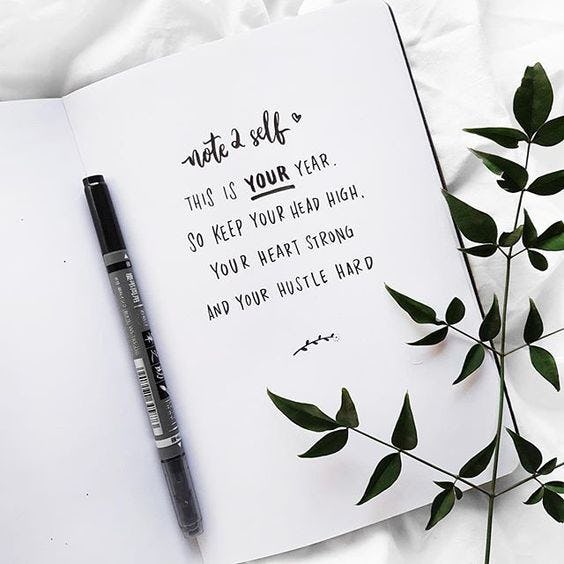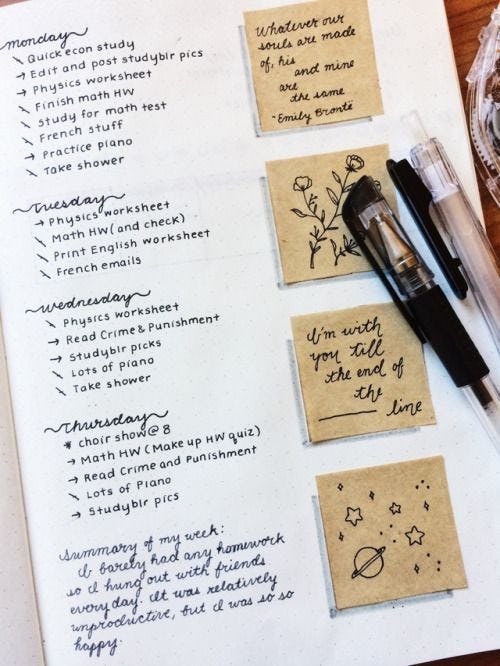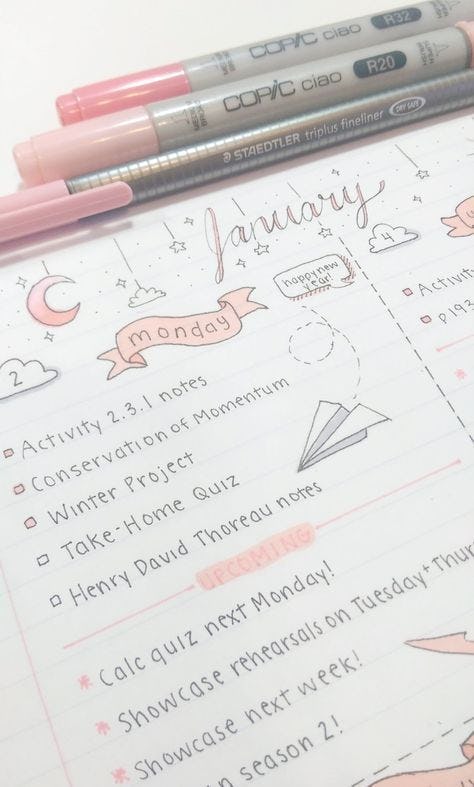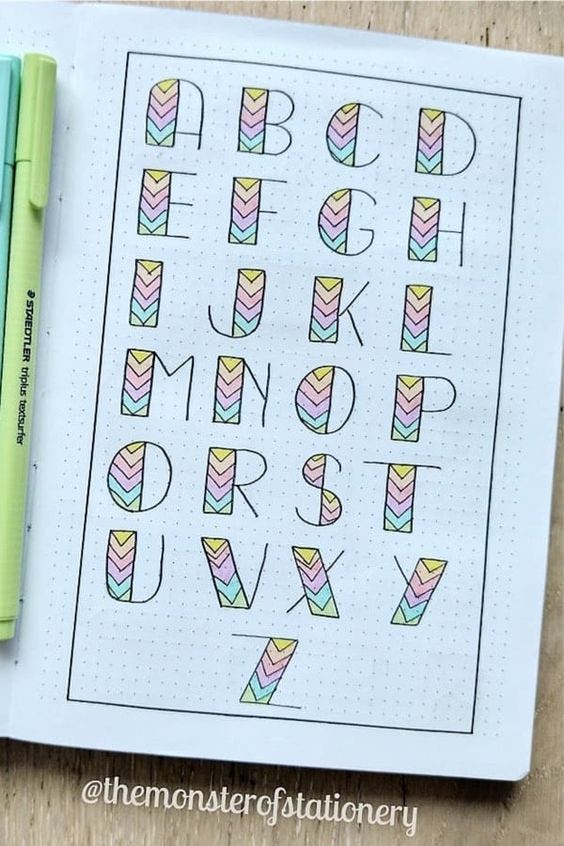
En otro artículo te contamos todo sobre el bullet journal: qué es, cómo hacerlo y para qué sirve. Hoy, te traemos las bullet journal fonts más lindas para que puedas empezar de inmediato a armar tu propia libreta.
En este artículo encontrarás más de 60 letras para bullet journal de las que te vas a enamorar. No hace falta que te dediques a la ilustración, con un poco de paciencia lograrás increíbles tipografías y tu bullet journal quedará espectacular.
¿Cómo elegir letras para bullet journal?
Si ya estuviste mirando algunos ejemplos de journals, seguramente te ha dado gran fascinación el grado de diseño y nivel decorativo que tienen algunos. Y en mayor parte, esto se debe a las bullet journal fonts que usan, ya que la tipografía es lo más importante en una libreta de este estilo.
Por eso, cuando empieces a diseñar la tuya, debes prestar mucha atención a qué tipografía vas a utilizar, de forma que quede bonita pero, a la vez, que no te lleve mucho tiempo escribir. Al fin y al cabo, ¿para qué sirve un bullet journal? ¡Para ayudarnos a gestionar mejor nuestro tiempo!
Lo principal que debes tener en cuenta es que hay tantas fuentes como temáticas para bullet journal. Por eso, lo ideal es que elijas tipos de letras que combinen con el diseño en general de tu journal.
Por ejemplo, si estás pensando en un diseño con flores, podrías agregar a tu listado de bullet journal fonts, algunas letras cursivas o con línea fina, y descartar opciones futuristas o con dibujos.
Bullet journal fonts: elementos que necesitarás
Otro aspecto que habrás notado, es que algunas fuentes tienen trazos más gruesos que otros y que en muchos de los diseños de bullet journal se utilizan una variedad de colores. ¿A qué vamos con esto? A que necesitarás algunos materiales básicos para poder hacer tus letras y que queden increíbles.
Así que toma nota de los elementos que necesitarás conseguir o comprar antes de empezar a diseñar tus bullet journal fonts.
✔️ Papeles o cuaderno: obviamente necesitarás tu bullet journal, pero además te recomendamos tener a mano hojas o un cuaderno de dibujo para practicar las letras.
✔️ Rotuladores para lettering: lo ideal es que cuentas con varias opciones de rotuladores. Estos pueden ser de punta pincel, punta rígida, caligráficos y de punta biselada.
✔️ Lápiz y goma de borrar: para que las bullet journal fonts queden perfectas, no te puede faltar este dúo.
✔️ Regla: un elemento básico del lettering.
✔️ Moldes de letras para copiar: algunas tipografías incluyen moldes o guías para replicarlas. ¡Puedes empezar a crear tus propias bullet journal fonts con ayuda!
En el caso de ilustradores profesionales, que quieran realizar sus plantillas de bullet journal de forma digital, necesitarán, obviamente, su tableta gráfica y algún programa de diseño, como Illustrator o Procreate.
Bullet journal fonts: estilos de letras
El cielo es el límite cuando de estilos de tipografía se trata. Hay tantas opciones, que puedes pasar horas viendo ejemplos y tratando de decidir.
Como predica el método BuJo, pongamos orden a nuestros pensamientos y veamos los tipos de letras que podrás usar para un bullet journal. Estas son las fuentes más habituales:
➡️ Fuentes serif
➡️ Fuentes san serif
➡️ Fuentes en cursiva
➡️ Fuentes con líneas
➡️ Fuentes en mayúscula
➡️ Fuentes con estilo globo
➡️ Fuentes en 3D
➡️ Fuentes finas
➡️ Fuentes con puntos o garabatos
¿Se te complica elegir? No te preocupes, no tienes que elegir solo un estilo. Por el contrario, puedes elegir varios estilos de bullet journal fonts y combinarlos.
Bullet journal fonts: letras para títulos y textos
Otro aspecto importante a considerar es la organización de lo que será tu bullet journal. Por ello, deberás tener en cuenta qué fuentes para títulos o grandes encabezados usarás. Por otro lado, también deberás pensar en letras para texto, frases y recordatorios.
Títulos de bullet journal
A continuación, te dejamos más de 50 ideas de bullet journal fonts para replicar en títulos:
Tipografías para textos largos y frases
También, te compartimos algunas bullet journal fonts para usar en textos largos y frases:
Como puedes ver, hay un montón de letras para títulos bonitos, como así también para textos en general, que puedes recrear para tu bullet journal. Lo ideal es que optes por una que no te demande demasiado esfuerzo y te sea sencilla y divertida de realizar, así sepas o no cómo hacer lettering.
✔️ Líneas divisorias
✔️ Recuadros para texto
✔️ Íconos
✔️ Decoraciones en general
Ya sea que optes por plantillas de bullet journal para imprimir, hagas tus propios diseños o mezcles un poco de ambas posibilidades, lo importante es que luego de leer este artículo, te quedes con muchas ideas e inspiración para replicar en tu cuaderno.